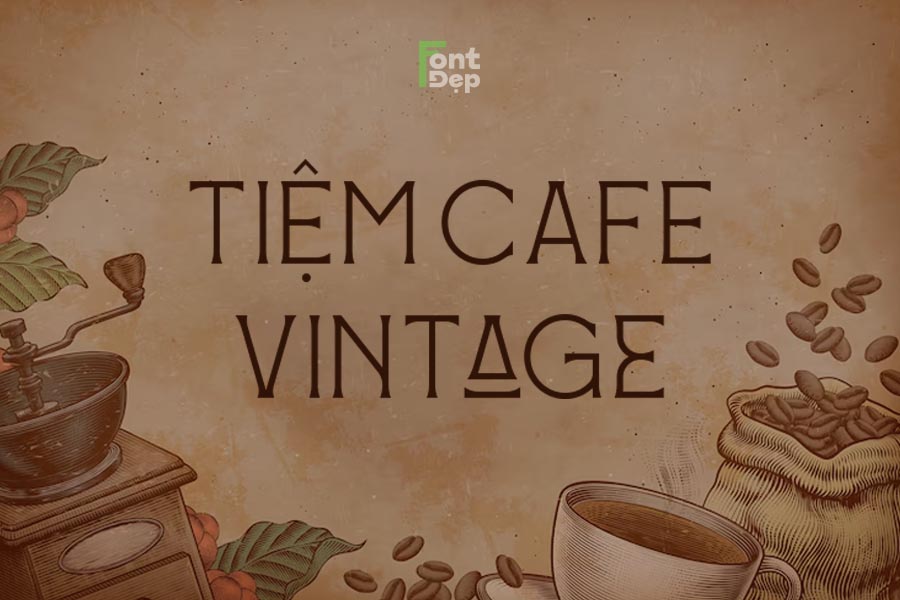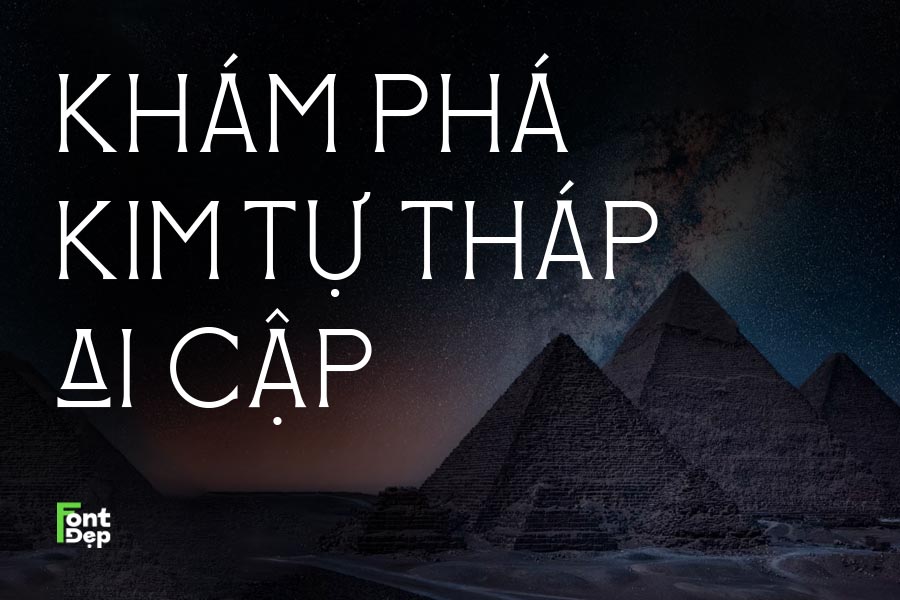
Font phong cách cổ điển Việt hóa TH Mackenzin
Nếu bạn đang tìm kiếm một font chữ mang vẻ đẹp cổ điển nhưng vẫn tinh tế và hiện đại, thì TH Mackenzin chính là lựa chọn không thể bỏ qua. Bộ font này đã được Việt hóa hoàn chỉnh bởi đội ngũ S99.VN, hỗ trợ đầy đủ dấu tiếng Việt, tối ưu cho cả in ấn lẫn thiết kế số.
Ngay từ cái nhìn đầu tiên, TH Mackenzin gây ấn tượng bởi kiểu dáng serif truyền thống, gợi nhớ đến những dòng chữ được khắc trên đá trong các công trình kiến trúc La Mã xưa. Các nét chữ được thiết kế đối xứng, thanh mảnh và gãy gọn. Phần chân chữ (serif) được xử lý nhẹ nhàng, không quá cầu kỳ nhưng vẫn đủ để tạo cảm giác sang trọng và chuẩn mực. Điều này giúp font dễ sử dụng trong nhiều bối cảnh mà không gây rối mắt.
Điểm nhấn đặc biệt của TH Mackenzin nằm ở những nét cách điệu tinh tế – chẳng hạn như ký tự “O” và “Ơ” với đường cắt chéo mềm mại, tạo nên điểm nhấn thị giác độc đáo. Những chi tiết này không chỉ khiến bộ font trở nên ấn tượng hơn, mà còn mang hơi thở nghệ thuật cổ điển pha hiện đại, phù hợp cho các thiết kế cần chiều sâu lịch sử và tính thẩm mỹ cao.
Với bản Việt hóa đến từ S99.VN, font được cân chỉnh từng dấu thanh như sắc, huyền, hỏi, ngã… một cách chỉn chu, đảm bảo trải nghiệm thị giác hài hòa và chuyên nghiệp. Dù bạn dùng trong tiêu đề, trích dẫn hay body text lớn, font vẫn giữ được độ rõ nét và sự cân đối cần thiết.
Nếu bạn là người yêu thích sự cổ điển nhưng không muốn bị gò bó bởi những font quá nghiêm nghị, TH Mackenzin là lựa chọn lý tưởng, vừa có bản sắc, vừa linh hoạt trong ứng dụng.